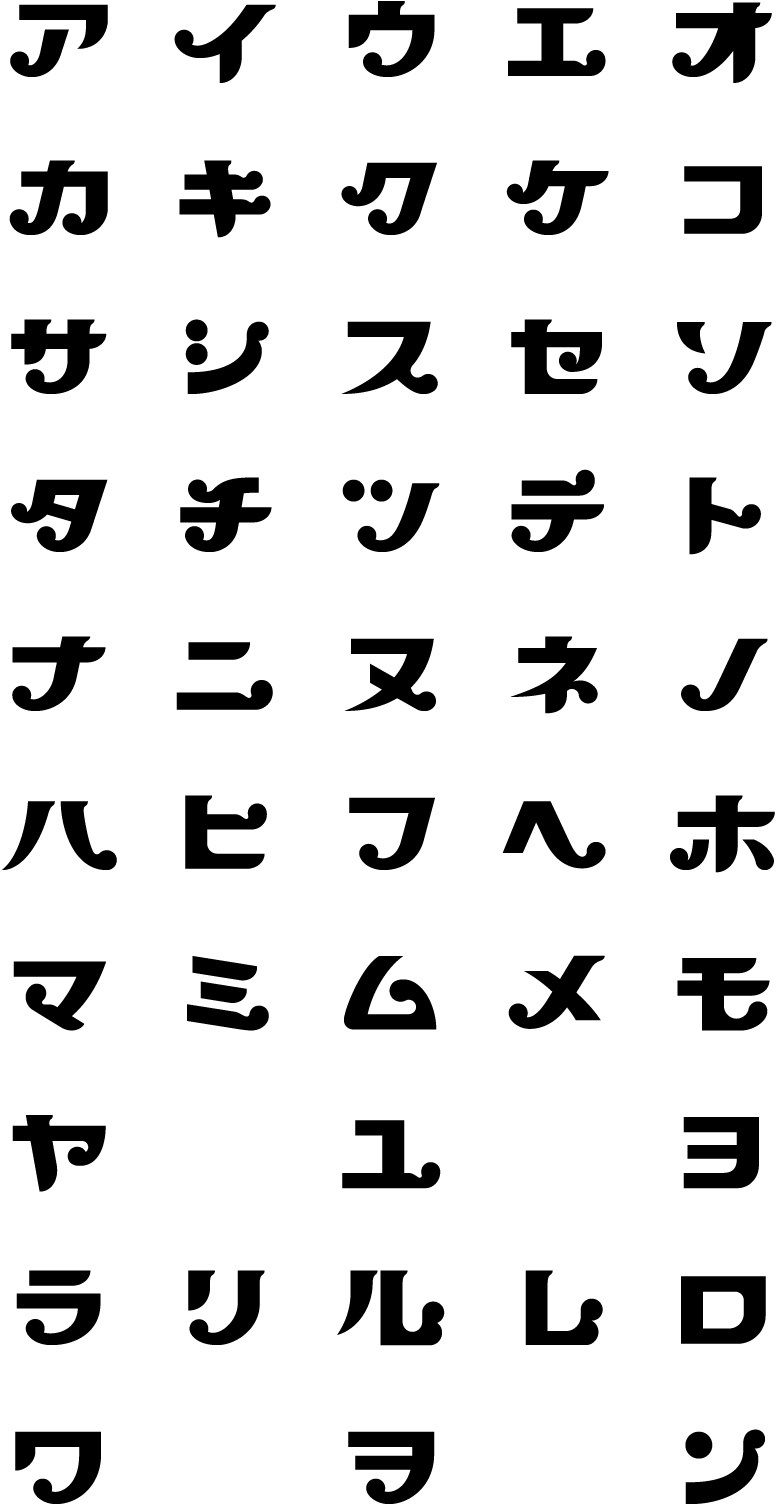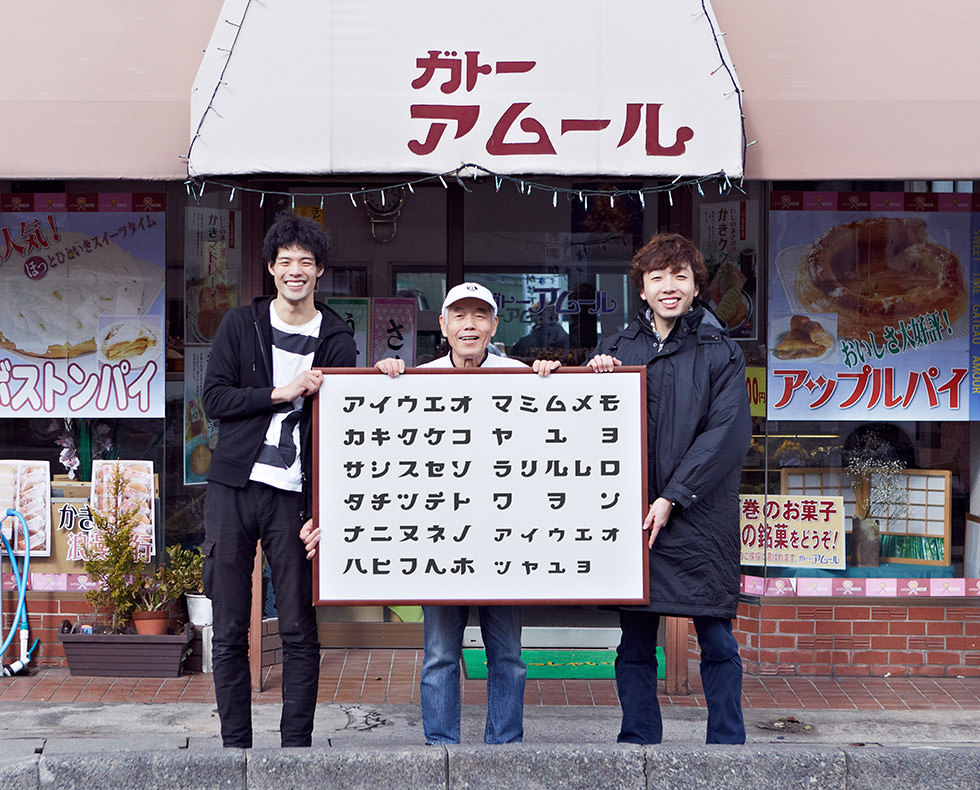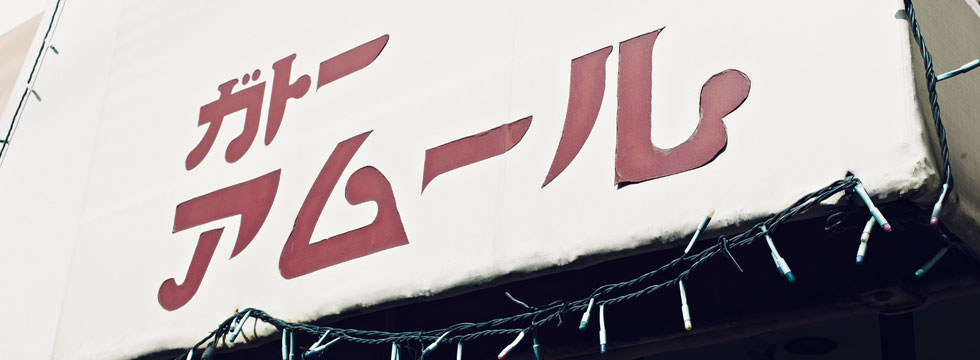
文字にフリーハンドの面白さがあり、整えすぎないことによる味わいがある。先端の丸みも特徴的。お菓子の甘いイメージを丸みに込めたのだろうか。
「アムール」は1971年に現店主の阿部さんが幸福堂(仙台にあった洋菓子店)での修行を経て、もともと父が経営していた洋菓子の卸業から製造業に転身して作ったお店だ。アムールという屋号の意味はフランス語で「幸福」。書体は包装紙を作るときに印刷会社の方がデザインしたものを採用した。以来ずっと使っているそうだが、アムールは石巻市の都市計画のため店舗を移動しなければならない可能性があるそうだ。「続けたとしても、いいとこ2、3年じゃないかね。やめるか、工場を小さくして続けるか、迷ってるっていうか。歳だしね。おれの母ちゃんだって、70だし。本当は若い人が継いでくれたらいいんだけどね。もし、ほとんど(土地を)とられても、ケースだけでも置いて商売できたらと思うけどね。とにかくやれるうちは、やる。」もし、移転しても今の書体の看板とともに、人々を幸福にするお菓子を作り続けてほしい。